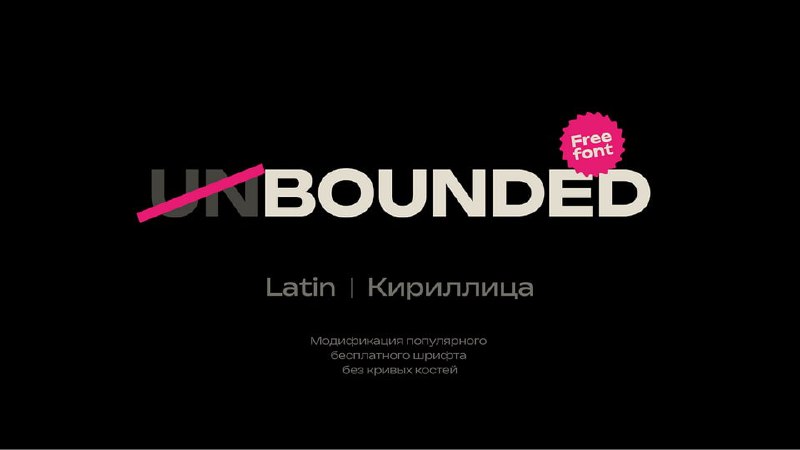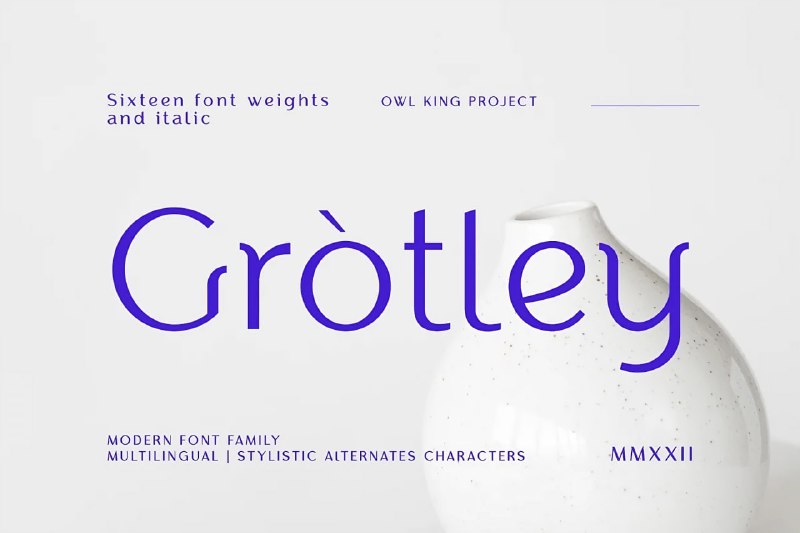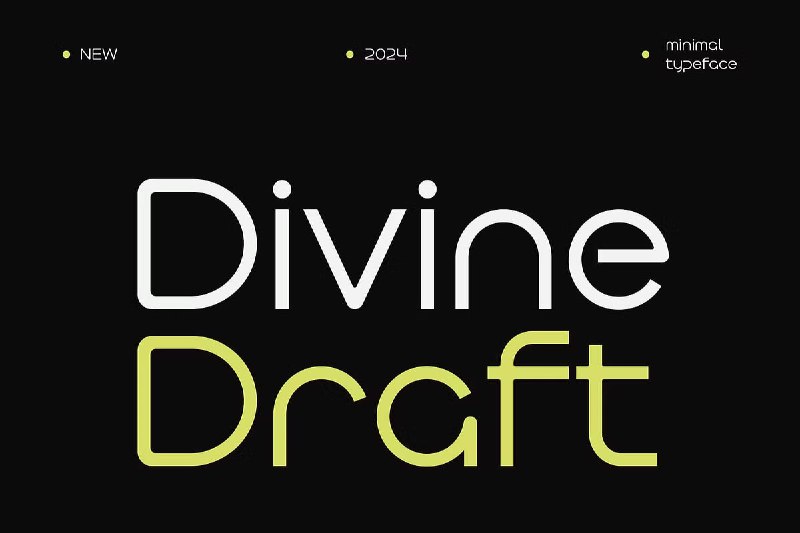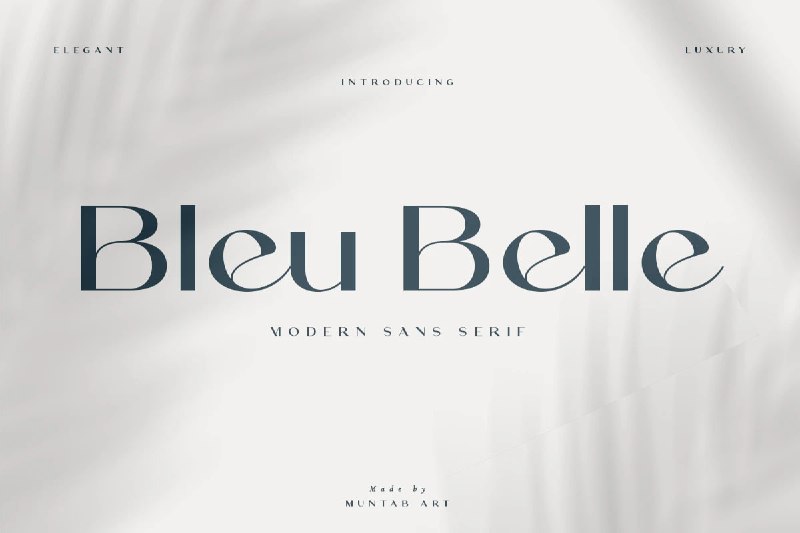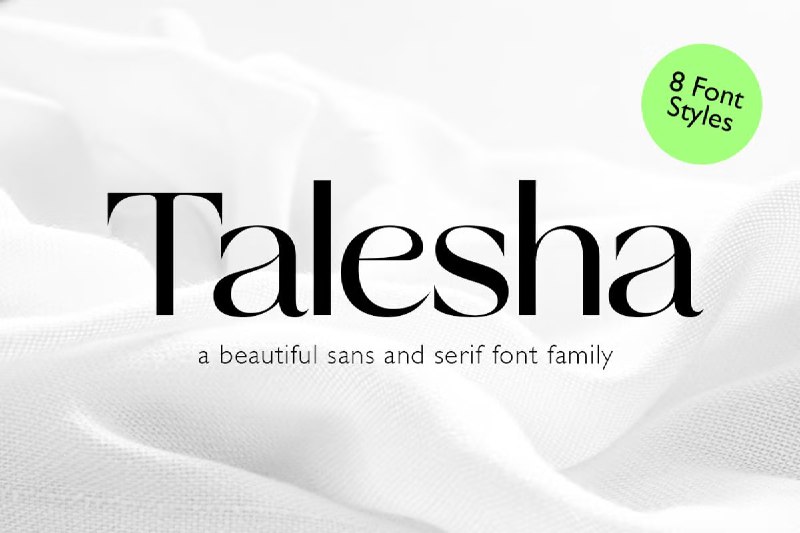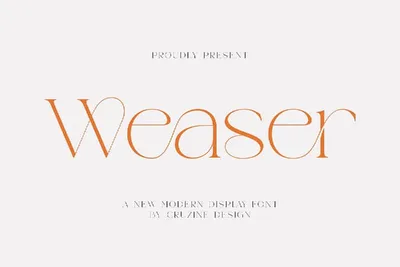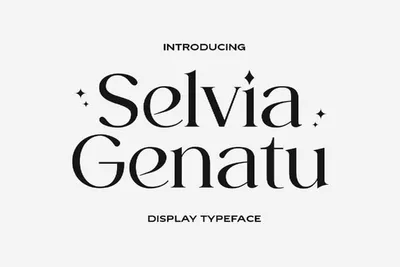
Шрифт "Talesha" Автор - Студия "Seniors" Страна - Индонезия 🇮🇩 Канал - Fonts Best Talesha - Это красивая на вид антиква, вдохновлённая старыми стилями 80-х годов. Не смотря на классические формы,
Шрифт "Bleu Belle" Автор "Muntab Art" Страна - Индонезия 🇮🇩 Канал - Fonts Best Красиивый такой вот шрифтец с чутка широкими формами и современным дизайном. Очень хорошо покажет себя в лого, бренди
Шрифт "Divine Draft" Автор - Студия "Hip Fonts" Страна - США 🇺🇸 Канал - Fonts Best Divine Draft — это мастерски разработанный минимальный шрифт, что воплощает в себе суть простоты и изысканности.
Шрифт "Grotley" Автор - "Owl King" Страна - Индонезия 🇮🇩 Канал - Fonts Best Grotley - Это семейство шрифтов, вдохновлено развитием мира моды и темой эксклюзивного места отдыха. Данный шрифт имеет
Шрифт "Selvia Genatu" Автор - Группа "Yukita" Страна - Индонезия 🇮🇩 Канал - Fonts Best Наверное это один из самых красивых шрифтов что я встречал! Selvia - Элегантный и ненавязчивый шрифт с привле
Шрифт "unBounded" Автор — Vlad Churkin Страна — Россия🇷🇺 Канал — Fonts Best
Шрифт "Weaser" Дизайнер "Peter Olexa" Страна - Словакия 🇸🇰 Канал - Fonts Best Художественный заголовочный шрифт с роскошными формами и лигатурам!😑 Обычно работает в одиночку и в большом варианте.
Шрифт "Moonlight Breeze" Автор — Jolicia Type Страна — Индонезия🇮🇩 Канал — Fonts Best Позвольте вашим дизайна
Шрифт "Adgeo" Автор — Ahmet Demir Страна — Турция🇹🇷 Канал — Fonts Best Этот шрифт сразу узнаваем как смелый современный шрифт, который броса